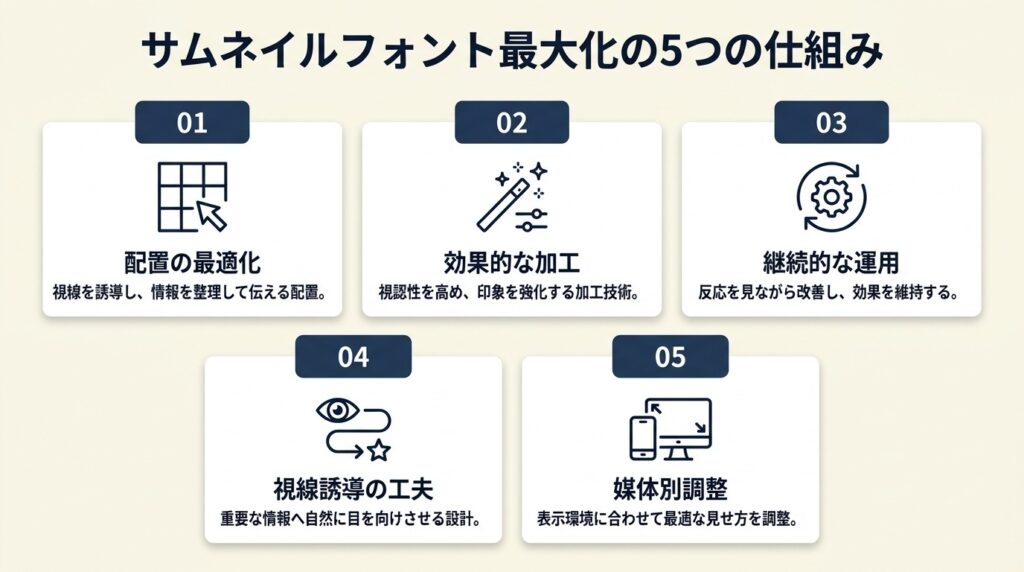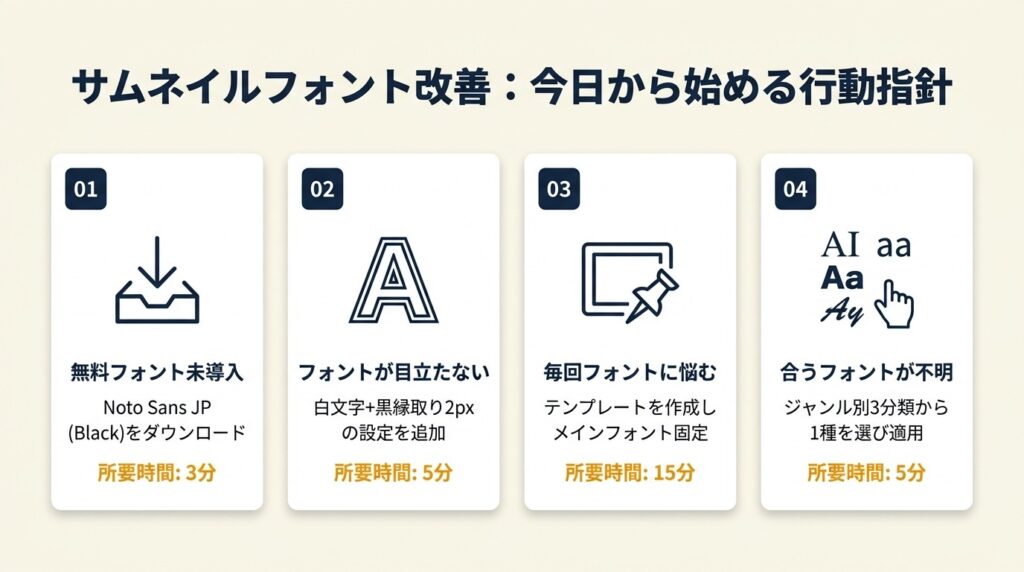
101チャンネル505本の実調査でわかったフォント1位はヒラギノ角ゴ(129本)。無料・商用OKで同等の視認性を持つNoto Sans JP Blackを今日から使える。2フォント構成に絞るだけでCTRが安定する。
YouTubeサムネイルのフォント選びでクリック率は変わります。101チャンネル505本の実調査では、ヒラギノ角ゴとけいふぉんと!が上位を占めました。この記事では無料・商用OKフォント7選と選び方を解説します。
この記事の結論
サムネイルフォントはHeavy/Bold以上のゴシック体を軸に選ぶことが、クリック率向上の最短ルートです。101チャンネルの実調査では、ヒラギノ角ゴがフォントなしと並んで1位を獲得しており、太さと視認性が支持される理由です。無料で商用利用できる源ノ角ゴシック HeavyやNoto Sans JP Boldを基本にし、ジャンルに応じてアクセントフォントを1種加える2フォント構成が、実務上もっとも再現性が高い方法です。
今日やるべき1つ
サムネイルフォントは実調査で2強が判明
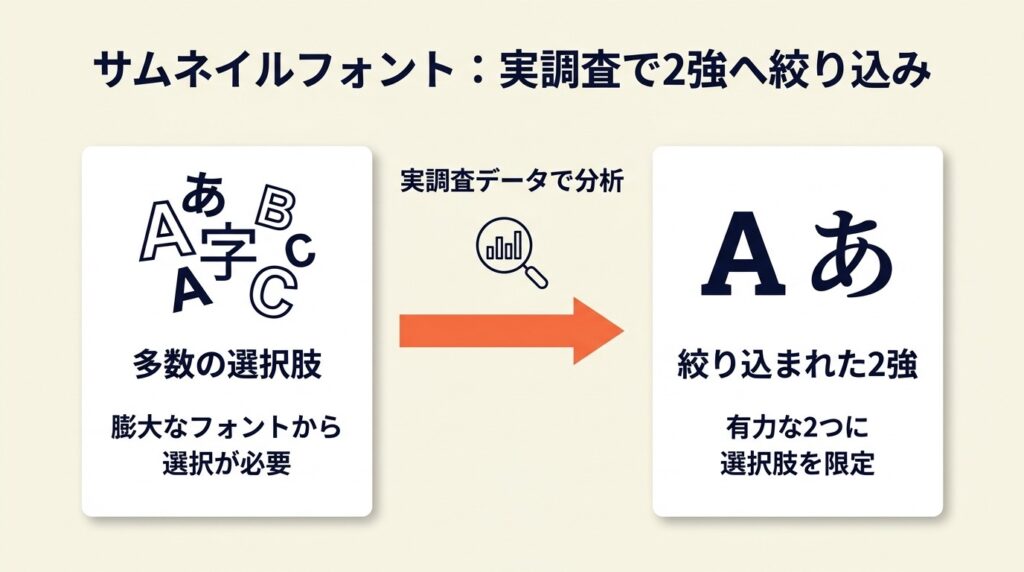
まず実際のデータを見ることで、選択肢を大幅に絞ることができます。
ヒラギノ角ゴは129本で堂々1位
101チャンネル・505本のサムネイルを実際に調査した結果、ヒラギノ角ゴとフォントなし(画像のみ)が同率1位の129本を占めることがわかっています(YouTubeで使われているフォントを調べてランキングを作った)。全体の約25%のサムネイルがこの2択に集中しており、フォント選びに悩む前にヒラギノ角ゴを試すことが最もリスクの低い出発点です。
YouTubeで使われているフォントを調べてランキングを作ったによると、「サムネイルはフォントバリエーション豊富で72ファミリー、インパクト重視でデザイン性高いものを多用」とされています。
ヒラギノ角ゴはMacに標準搭載されているため、Mac利用者はすぐに使える点が強みです。Windowsでは有料購入が必要になるため、次項の源ノ角ゴシックが代替として機能します。サムネイル作成と並行して画像に文字入れできる無料ツールを活用すると、フォント設定から仕上げまでブラウザで完結できます。
けいふぉんと!は16本で装飾系トップ
調査の3位はけいふぉんと!(16本)、4位は凸版文久見出し明朝(15本)でした。けいふぉんと!はゲーム・エンタメ系チャンネルで特に多用されており、手書き風の太いラインがサムネイルに躍動感を与えます。凸版文久見出し明朝はビジネスや教育系でブランドの信頼感を演出する用途に向いています。この2種は、ヒラギノ角ゴをメインに据えた上でジャンルに応じて入れ替えるサブフォントとして検討できます。
フォントなし選択肢も25%を占める事実
「フォントなし」が同率1位という結果は見落としがちですが、画像そのもののインパクトで勝負できるケースが一定数存在することを意味します。顔写真やビフォーアフター画像を使うサムネイルでは、文字を入れることで逆にノイズになる場合があり、フォント選びよりも画像の質を先に見直すことが正解になることもあります。背景素材の質を高めたい場合は無料で商用利用できる背景素材サイトを参照してください。
Q: ヒラギノ角ゴはWindowsで使えますか?
A: Windowsでは有料のライセンス購入が必要です。無料の代替として源ノ角ゴシック HeavyまたはNoto Sans JP Boldが同等の視認性を持ち、商用利用も無料で可能です。
Q: フォントなしサムネイルはSEOに影響しますか?
A: YouTubeのSEOはサムネイルの文字の有無に直接影響しません。ただし、テキストがあることでABテスト(サムネイルテスト機能)での差別化がしやすくなるため、クリック率改善の検証目的ではフォントありを推奨します。
サムネイルフォントは7種で網羅
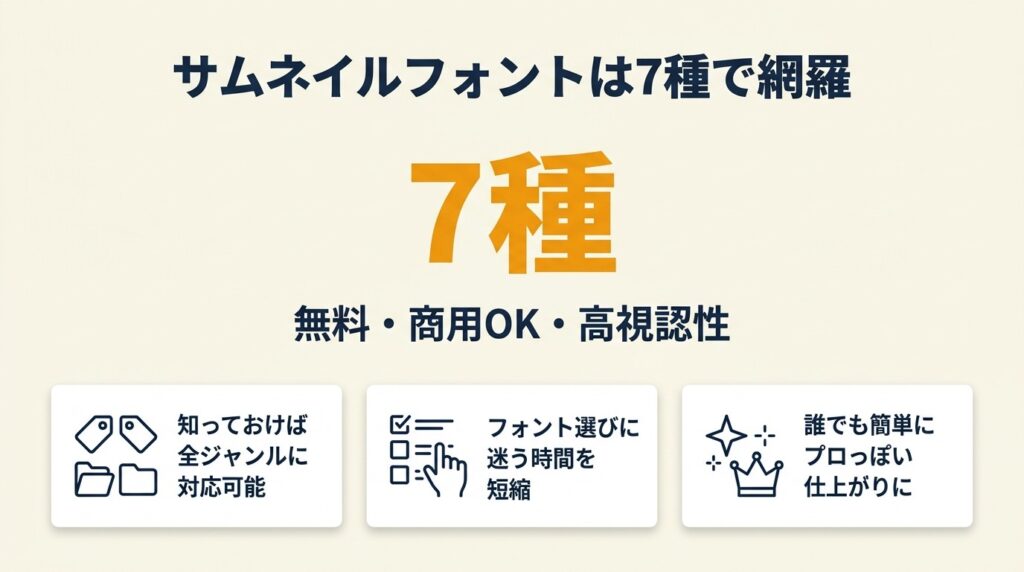
無料・商用OKの条件を満たしながら高い視認性を持つフォントは7種に絞ることができます。これだけ知っておけば、ジャンルを問わず対応できます。
ゴシック系は源ノ角ゴシックが最優先
源ノ角ゴシック Heavy(別名:Adobe Source Han Sans)はGoogle・Adobe共同開発のオープンソースフォントで、個人・商用ともに無料で利用できます(Google Fonts – Noto Sans JP)。太さウェイトが7段階あり、サムネイルにはHeavy(最太)の使用が推奨されます。
クリック率UP フォント18選によると、「源ノ角ゴシック Heavyはどんな背景でも読みやすく、ビジネス系で信頼感を与える」とされています。
ビジネス・教育・Vlog・技術系など汎用性が高く、初めて無料フォントを試す場合の第一選択です。源ノ角ゴシック HeavyはGoogleフォントの「Noto Sans JP」として取得できるため、OSを選ばず利用できる点が他のフォントにはない最大の実用メリットです。日本語フォントを無料で活用する方法も合わせて確認しておくと、フォント管理の手間を減らせます。
明朝系・装飾系は用途限定で追加
明朝体の中では凸版文久見出し明朝(無料・商用OK)が、読みやすさとインパクトを両立する数少ない選択肢です。通常の明朝体はサムネイルでは線が細く埋もれやすいですが、凸版文久見出し明朝は見出し専用に設計されているため縦横の線の太さバランスが調整されており、1280×720pxの解像度でも識別できます。装飾フォントであるけいふぉんと!や源暎ポップル・はちまるポップは、サムネイル全文字への適用ではなく、1〜2文字のアクセント使いに限定するのが誤用を防ぐ基準です。
英語フォントはBebas Neueで完結
英語タイトルまたは日英混在のサムネイルには、Bebas Neue(Google Fonts、無料・商用OK)が実務上の標準です。全大文字のディスプレイフォントでモバイル画面の小表示でも視認性が落ちにくく、海外クリエイターのサムネイルでも高頻度で使われています。日本語フォントと組み合わせる際は、日本語を源ノ角ゴシック Heavy・英数字をBebas Neueに割り当てる分業がもっとも違和感の少ない組み合わせです。かっこいい数字フォントの選び方も参考にすると、数字を含むサムネイルの視認性をさらに高められます。
Q: フォントは何種類まで1枚のサムネイルに使えますか?
A: 原則2種類が視認性と統一感を両立する上限です。メインフォント(ゴシック系)とアクセントフォント(装飾系)の2役に役割を分けることで、ごちゃついた印象を防ぎます。
Q: 源ノ角ゴシックとNoto Sans JPは別のフォントですか?
A: 実質的には同一フォントです。GoogleがNoto Sans JP、AdobeがSource Han Sansという名称でそれぞれ配布していますが、フォントデータは共同開発されており字形は共通です。Googleフォント経由で取得する場合は「Noto Sans JP」で検索してください。
サムネイルフォントの選び方を3分で診断
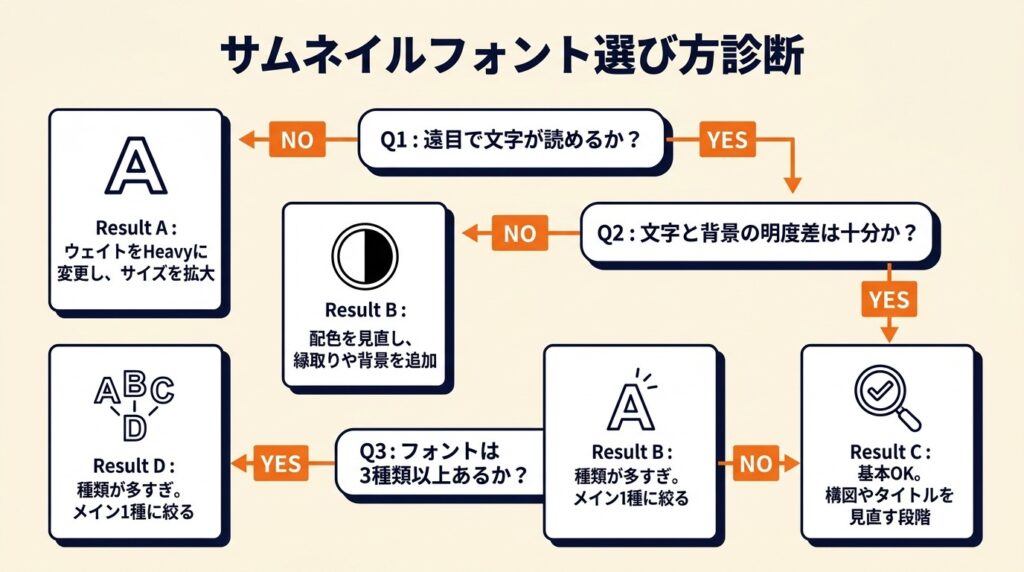
「フォントを変えてもクリック率が上がらない」という状況は、フォントそのものより選び方の基準にズレがあるケースが大半です。次の質問で自分の状況を確認してください。
Q1: サムネイルの文字は遠目(スマートフォン画面から30cm離れた状態)で読めますか?
読める場合はQ2へ進んでください。読めない場合はResult Aです。フォントウェイトをHeavyに変更し、文字サイズを最低でもサムネイル高さの15%以上に設定してください。現在使っているフォントがBold未満のウェイトである可能性が高く、まず源ノ角ゴシック HeavyまたはNoto Sans JP Blackへの変更が優先です。
Q2: フォントの色と背景の明度差は十分ですか?(白文字+暗背景、または黒文字+明背景など)
十分ある場合はQ3へ進んでください。不十分な場合はResult Bです。視認性の問題はフォント選びよりも配色に起因しています。フォントを変える前に、文字に2px以上の黒または白の縁取り(アウトライン)を追加するか、文字背景にテキストボックスを敷く対処が先決です。
Q3: 使用しているフォントは1枚のサムネイルに3種類以上ありますか?
2種類以下の場合はResult Cです。フォント選択・コントラストの基本は満たせています。クリック率が伸びない場合、フォントよりもサムネイルの構図(人物の顔・感情表現・数字の大きさ)やタイトルテキストの内容を見直す段階です。3種類以上の場合はResult Dです。フォントの種類が多すぎて視線が分散しています。メインフォント1種に絞り、残りを削除するだけでクリック率が改善するケースが多くあります。
CHECK
▶ 今すぐやること: スマートフォンのYouTubeアプリを開き、自分のサムネイルを検索結果一覧に表示させて文字の可読性を確認する(2分)
よくある質問
Q: クリック率の目標値はどのくらいに設定すればいいですか?
A: YouTube Studioのアナリティクスでは、インプレッションのクリック率(CTR)の中央値は2〜5%程度とされています。自分のチャンネルの過去30日平均を基準に、フォント変更前後で比較する相対評価が実用的です。
Q: サムネイルABテストはどのように行いますか?
A: YouTube Studioの「サムネイルテスト」機能(一部チャンネルで提供中)を使うか、同テーマで2本の動画を異なるサムネイルで公開し、7日間のCTRを比較する方法が現実的です。フォントを1変数に絞ることで、差の原因を特定しやすくなります。
サムネイルフォントはジャンル別に3分類
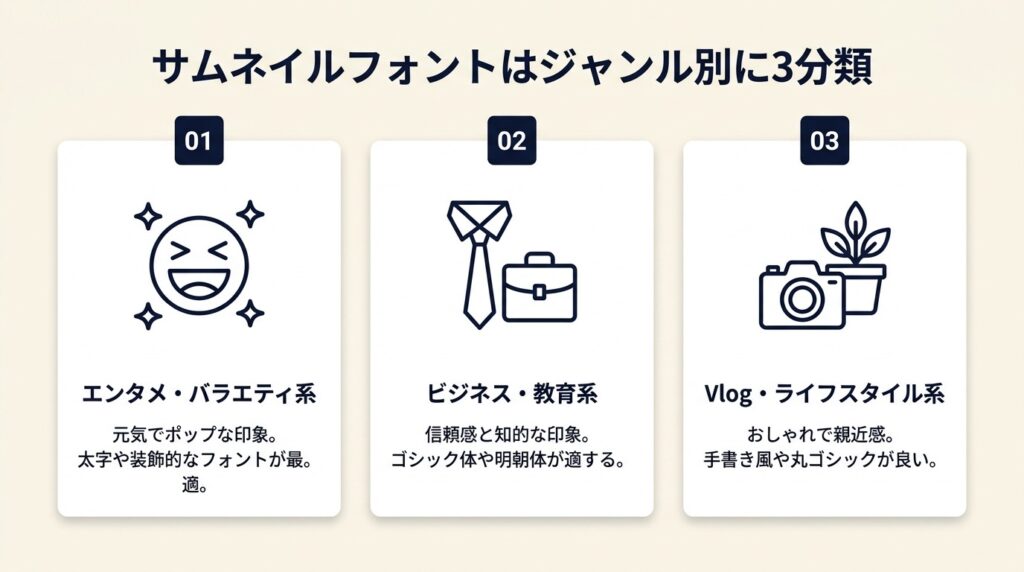
チャンネルのジャンルと視聴者像によって、最適なフォントの方向性は異なります。「人気フォントだから」という理由だけで選ぶと、チャンネルの雰囲気と文字のトーンが合わない問題が生じます。
Q: WindowsとMacでフォントの見た目は変わりますか?
A: ヒラギノ角ゴはMacに標準搭載されているためMac環境では追加費用なしで使えますが、Windowsでは有料です。Noto Sans JPやBebas NeueはGoogleフォントからOSを問わず無料取得できるため、Windowsユーザーは源ノ角ゴシック Heavy(Noto Sans JP)をヒラギノの代替として使用してください。レンダリング(フォントの描画品質)はOSによって若干異なりますが、HeavyウェイトではMac・Windows間の差は実用上問題のないレベルです。
Q: フォントを変えたらすぐにクリック率は上がりますか?
A: フォント変更の効果が数値に現れるまで最低7〜14日(インプレッション数が1,000回以上になるまで)の計測期間が必要です。変更直後のデータは母数が少なく判断材料として不十分なため、変更後2週間のCTR平均と変更前2週間の平均を比較する方法が適切です。